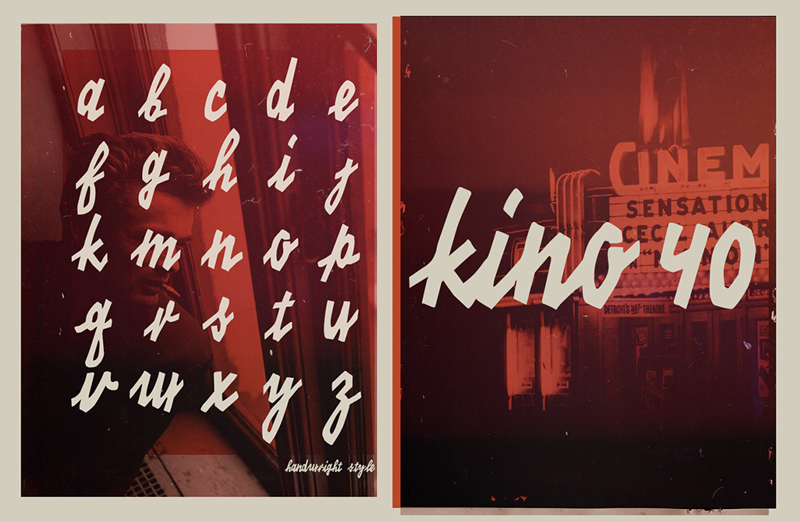
KINO 40 es una de esas fuentes que te recuerdan a los viejos posters de películas antiguas. Su creador es un Alemán cuyo perfil en Behance es el siguiente: https://www.behance.net/les83machines